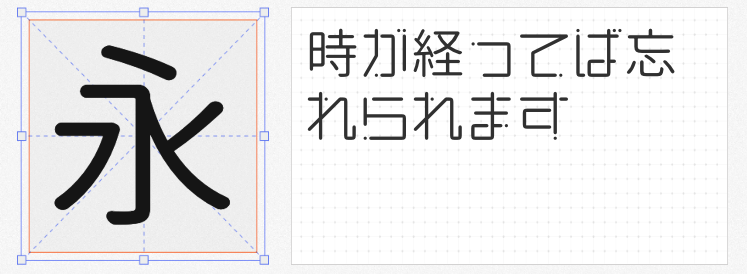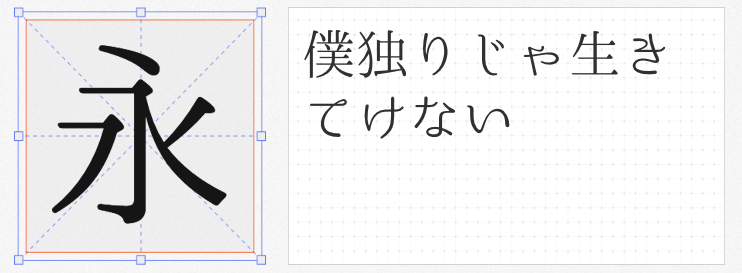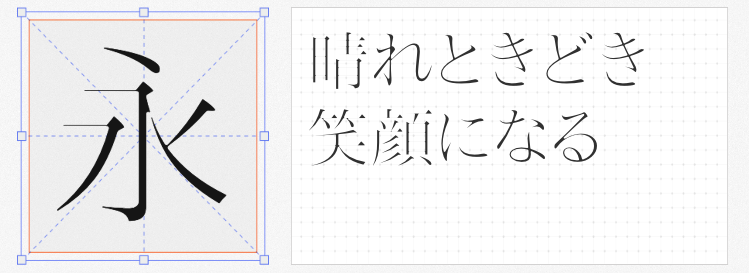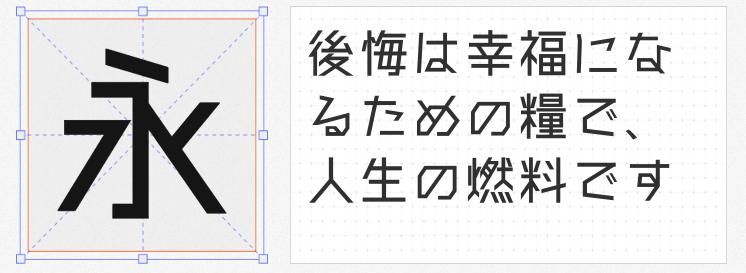
在设计中,日文字体凭借其独特的结构与风格,成为提升视觉表现力的关键元素。本文精选四款免费可商用的日系字体,从古典到现代、从刚硬到圆润,满足不同场景的设计需求。
这款字体以“横排连接感”为核心设计理念,在保留古典明朝体的柔和、复古风味与汉字假名平衡的基础上,通过笔直垂直线、水平线及斜线设计,赋予字体现代感。其笔触清晰,横竖笔画粗细对比适中,适合书籍排版、海报标题及品牌VI设计,尤其适合需要横竖混排的场景。该字体曾获日本印刷年鉴最佳作品奖,兼容中日韩统一表意文字,支持GBK编码,可广泛应用于出版物、包装及网页设计。
基于IPA明朝体衍生的晴空明朝Thin,以极细横笔画为特色,整体字形刚硬方正,适合文化宣传类设计。其七重字重(从极细到极粗)可灵活应对不同场景需求,如标题大字或正文排版。尽管部分中文字符可能无法识别,但其日文汉字覆盖率较高,适合中日双语设计项目。
这款字体以完全直线化的笔画设计著称,无弧度、无圆角,呈现出强烈的几何感与工业风。其字形修长,适合需要突出科技感或未来感的设计,如机械、游戏、科幻类海报或产品包装。尽管对简体中文支持有限,但繁体中文覆盖全面,适合港台地区设计需求。
灵感源自动画《恋爱小行星》的恋星圆体α,以“直线圆润”为特色,下边缘与上边框对齐,兼具现代感与亲和力。其字形中融入小行星天文符号,适合女性向、青春类设计,如动漫周边、文创产品或社交媒体海报。该字体采用SIL Open Font License授权,支持繁体中文与日文,适合需要传递温暖与趣味性的场景。
四款字体各具特色。无论是商业项目还是个人创作,这些免费可商用的日系字体都能为设计注入独特的视觉感受。